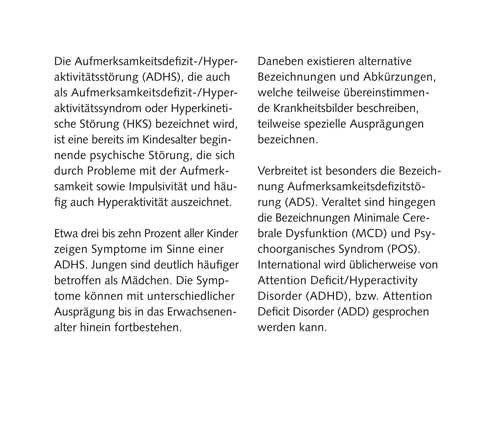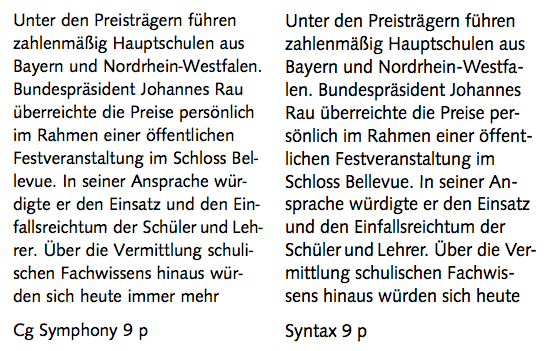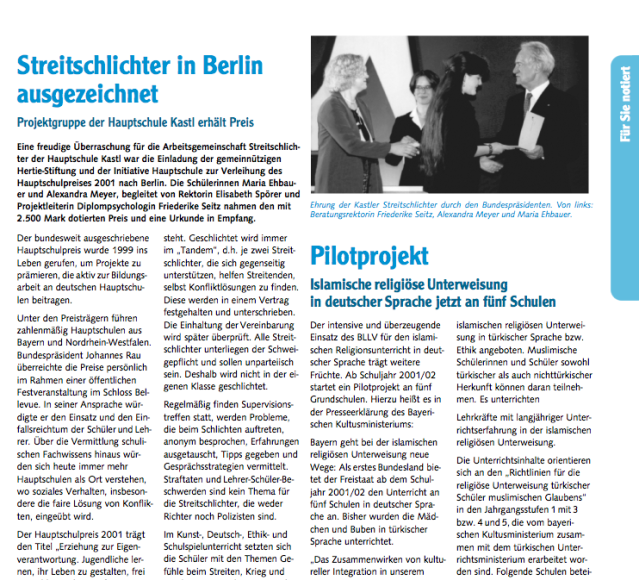
Flattersatz bei geringer Spaltenbreite
so langsam bin ich der Ansicht, dass Flattersatz nur komplett manuell zu machen ist. Rohfassung:
Was muss ich einstellen, wie muss ich vorgehen (Tastenkombinationen), damit das was wird? Oder sind die Spaltenbreiten gänzlich ungeeignet?
Konstanten: Syntax, 9/12, Spaltenbreite 50mm.
9 pt bei 50 mm Spaltenbreite ist nicht mal für Marginalien geeignet. Nimm die beiden Spalten zusammen zu einer, dann wird’s auch was.
Bei kleinformatigen Booklets für Zeitschriften habe ich leider häufiger solche Vorgaben zu bewältigen, nicht immer ist es da erlaubt, Spalten einfach zusammenzufassen (Designrichtlinien Kunde). Ich muss sagen, ich gleiche dann wirklich immer per Augenmaß und Hand aus, feste Einstellungen sind dabei oft zu starr und man braucht zu viele Ausnahmen von der Regel, beispielsweise, wenn Marken- oder Eigennamen vorkommen, die nicht getrennt werden dürfen. Nicht schön, aber Arbeitsalltag. :?
… Designrichtlinien Kunde …
Das würde ich dann nicht als Designrichtlinie bezeichnen, wenn dort solche Vorgaben gemacht werden. Vielleicht kannst du den Kunden in solchen Fällen von der Ausnahme überzeugen …
50 mm mit 9 pt und das noch mit der syntax ist einfach schlechte typografie.
ich verstehe den sinn der zweispalten in dem fall nicht so richtig?
bertl hat recht, eine spalte und dann wird es was.
das hat nichts mit einstellungen zu tun eher mit zu wenig erfahrung.
der gestltungsraster kann trotzdem zweispaltig bleiben, falls man da
bilder platzieren soll aber für den text und für den leser ist es einfach eine qual.
Hallo Bertel,
schön wär's! Aber der Kunde in dem von mir beschriebenen Fall ist zu groß (große deutsche Zeitschrift), und mein kleines Teilprojekt für ihn zu unbedeutend, als dass ich da an den Richtlinien rütteln könnte. Bei anderen Kunden rüttele ich dafür umso mehr. :)
Ja, manchmal geht’s einfach nicht, das kenne ich auch :? Schön, wenn dann anderenorts umso kräftiger gerüttelt wird, machen Kunden hat das sogar schon wachgerüttelt :D
Bei einer 9/12 Syntax mit einer Spaltenbreite von 50 mm würde ich nicht gerade von schlechter Typografie sprechen. Immerhin sind das ca. 32 Anschläge pro Zeile und durch den Flattersatz werden zu große Wortzwischenräume vermieden. Ein Problem für den Leser ergibt sich eher bei einer zu hohen Anzahl von Buchstaben pro Zeile (ab ca. 60 Buchstaben).
Das optisch unschöne Bild deiner Textprobe ist auf die zu vielen Absätze zurückzuführen.
Um fallweise bei der Zeilentrennung einzugreifen kommst du nicht umhin.
Ich muss Erwin Krump recht geben.
Mit ein wenig Mühe (okay, man muß schon jede Zeile beinflussen) kommt man auch auf
ein – für meine Begriffe – gutes Ergebnis.
Wer keine Trennungen mag, ist allerdings bestimmt nicht zu überzeugen. :)
Nein, das ist kein gutes Ergebnis. Für eine Marginalie mit 5 Zeilen ließe ich das noch durchgehen, aber nicht für einen Fließtext.
Man müsste die übrigen Elemente aus der sich diese Arbeit zusammensetzt kennen, um zu beurteilen, ob ein- oder zweispaltig sinnvoll ist. Ich wollte nur begründen, dass die Zeilenbreite von 50 mm mit einem Schriftgrad von 9/12 pt. nicht unüblich ist, wie übrigens unzählige Zeitungen, die nicht gerade das Papierformat der „Zeit“ aufweisen, belegen.
Das habe ich auch nicht behauptet. Die Zeilenbreite alleine macht sicher keine gute Typografie. Dazu gehört mehr.
Ich habe nun die Spaltenbreite um 10mm vergrößert und mich an einen händischen Flattersatz versucht:
- ich weiß aber gar nicht mehr hundertprozentig, ob wir bei der letzten Besprechung eine oder zwei Spalten wollten. :schonklar: Aber ich bin mir relativ sicher: Eine.
:tutor: Blackerl, sei mir nicht bös, aber das geht gar nicht. Weder Trennungen noch Zeilenlängen sind optimiert, das ist einfach nur hingeschüttet. Ich glaub fest an dich, dass du das besser kannst :trost:
Flatterbereich zu groß?
Es stellt sich kein Leserhytmus ein; sieht aus, als wär ein gleichmäßiger, aber harter kurz-lang-Wechsel angestrebt worden ...
Flatterbereich zu groß?
Es stellt sich kein Leserhytmus ein; sieht aus, als wär ein gleichmäßiger, aber harter kurz-lang-Wechsel angestrebt worden ...
Genau das habe ich gemacht. :D Dachte, alles andere wäre Rausatz.
Also, gerade wenn die beiden Spalten nebeneinander stehen, entsteht ein anstrengender Eindruck: unruhig für die Augen und anstrengend zu lesen.
Ich würde den Flattersatz deutlich beruhigen oder – wenn das Projekt Dir die gestalterische Freiheit lässt – auf eine Textspalte umsteigen. Zumal, wenn Du noch mehr Text zu setzen hast: doppelte Spaltenzahl = doppelte Arbeit mit dem Geflattere.
Flatterbereich zu groß?
Es stellt sich kein Leserhytmus ein; sieht aus, als wär ein gleichmäßiger, aber harter kurz-lang-Wechsel angestrebt worden ...
Ich dachte immer Maximum und Minimum bezieht sich nur auf den Blocksatz, während Optimum beim Flatter-/Rausatz zum tragen kommt?
Habe jetzt mal einen Rausatz (ohne manuelle Korrekturen) erstellt. Finde, er sieht (den Umständen entsprechend) ganz gut aus - oder? Der Trennbereich wurde auf nur 5mm gestellt.
Einspaltig sieht indes aus wie ein Liedtext in der Kirche - deswegen mache ich das nicht. Da müsste ich nämlich das Format ändern und das möchte ich nicht.